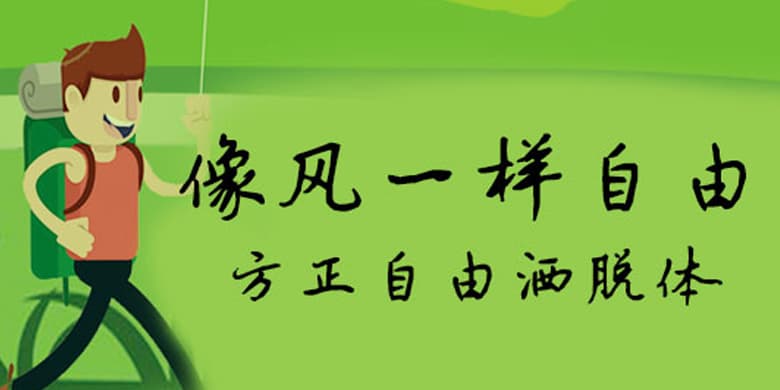
品牌:方正手迹设计师:周光艳发行时间:2020字库编码:大陆简体(GB2312-80)分类:常规书写·硬笔字体属性:精品字
这是一款充满力量的字体,笔画线条富于变化,有着行云流水般的写意书风。单字的结构舒展挺拔,排列在一起,有种娓娓道来的感觉,适用于文艺类的书刊、品牌广告和产品包装设计,以及社交网络的个性化用字。